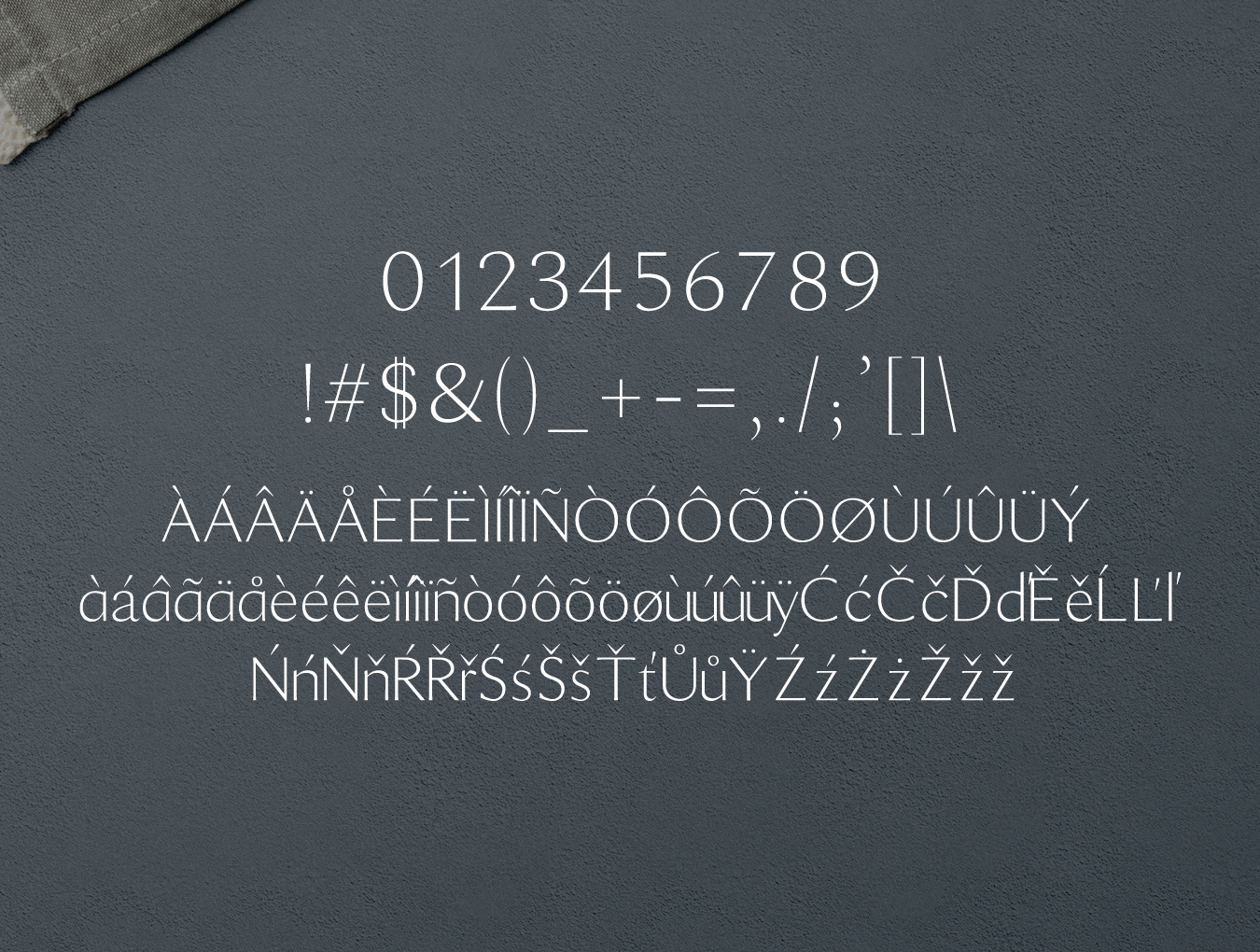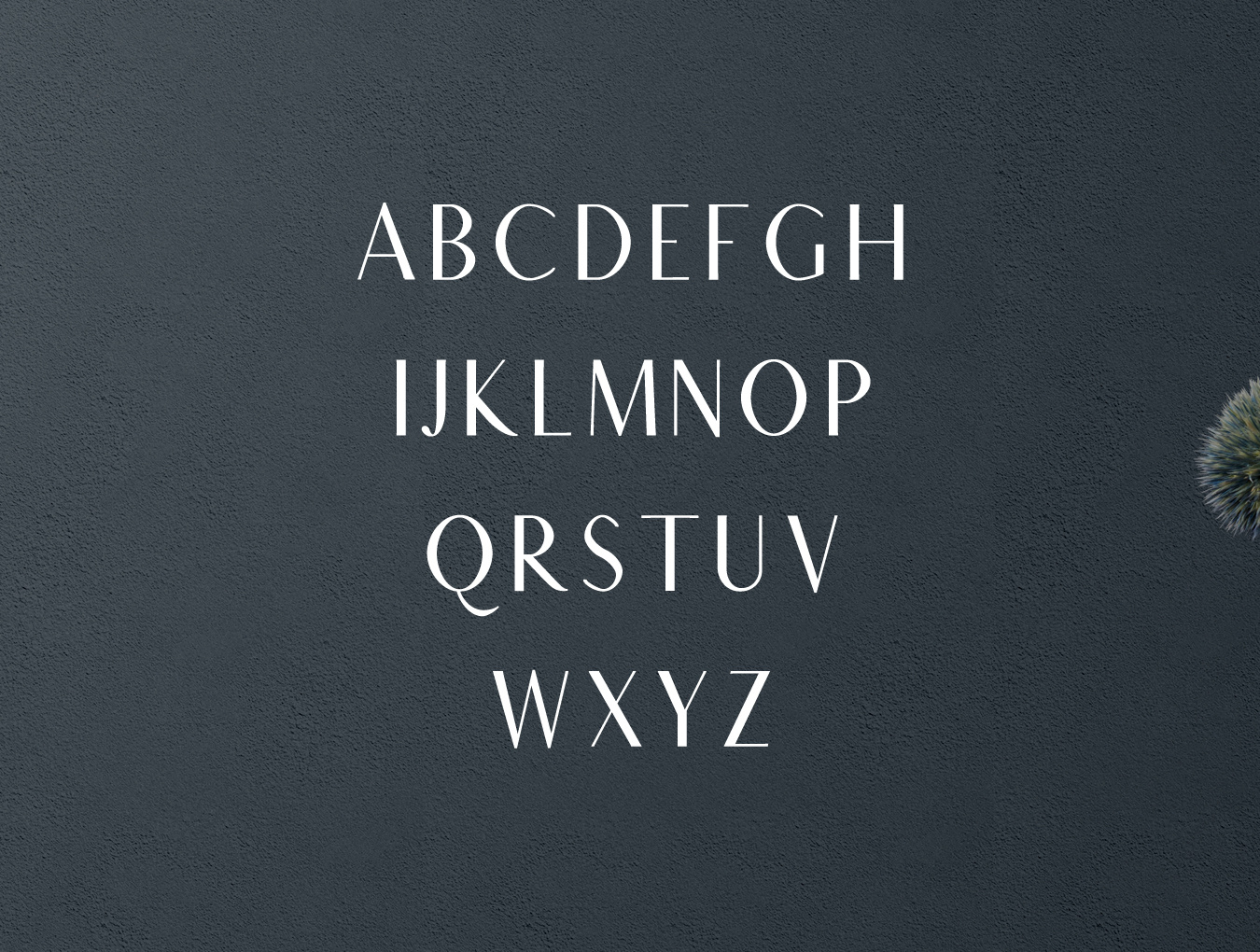
Maleah Sans Serif 2家庭装字体,Maleah Sans Serif
Maleah Sans Serif 2 Font Family Pack, Maleah Sans Serif
Maleah Sans Serif 2 Font Family Pack具有独特而现代的衬线外观和感觉。非常适合华丽的徽标,标题,网页布局和品牌。如果你想尝试一个优雅的外观,它看起来华丽,所有帽子都有宽大的间距,或者在大写字母和小写字母中完美无瑕。